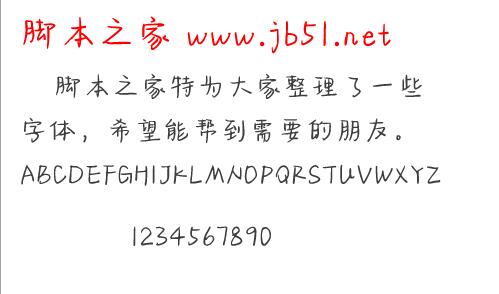
半糖咖啡字體是aa字體開發(fā)的一款非常不錯(cuò)的中文字體,該字體線條粗細(xì)適中,運(yùn)筆靈動快捷,但風(fēng)格上偏可愛、萌新的感覺,可以應(yīng)用于文本裝潢、信息展示、網(wǎng)頁設(shè)計(jì)、篆刻制模、數(shù)據(jù)制作、裝潢設(shè)計(jì)、計(jì)算藝術(shù)設(shè)計(jì)、視覺設(shè)計(jì)、字帖等一切合法應(yīng)用場景。